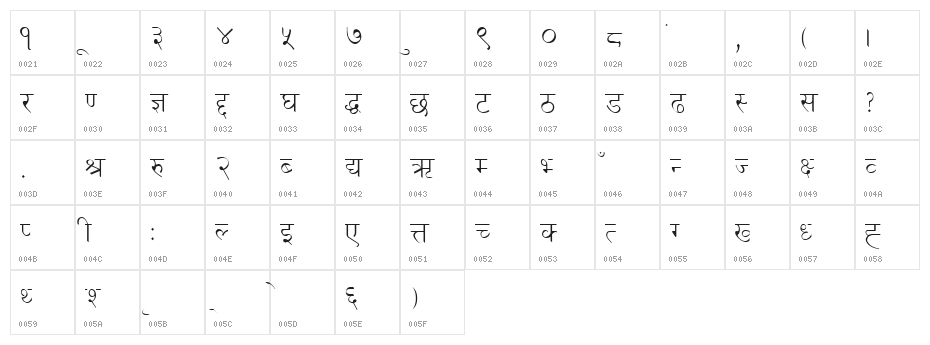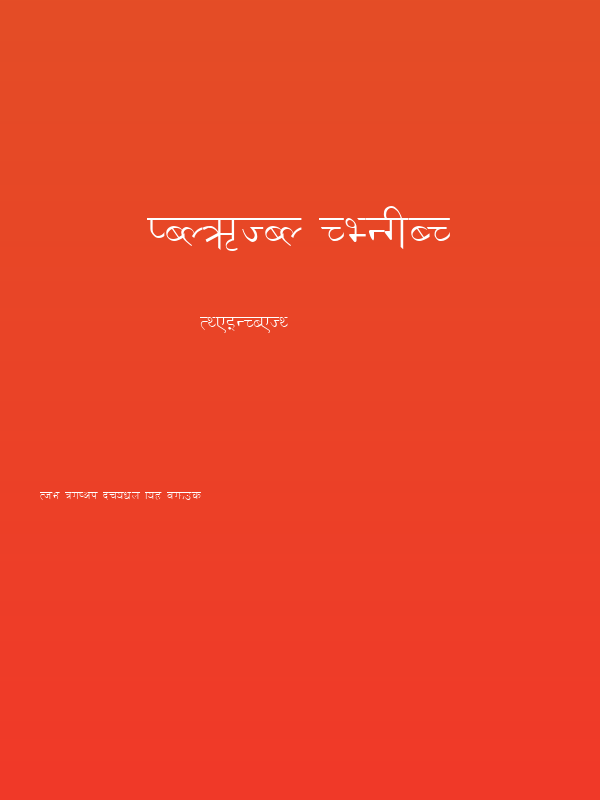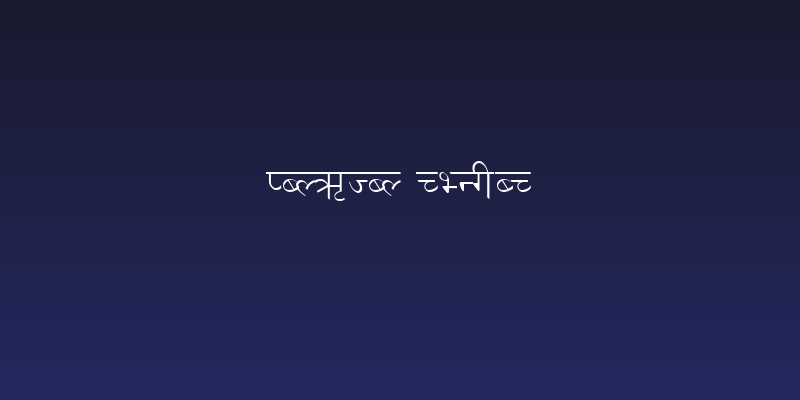
Kanchan Regular Font
✎ Calligraphic
| Категория | Calligraphic |
| Общий стиль | Classic |
| Область применения | Headlines, Artistic projects, Cultural publications |
| Рекомендуемые проекты | Ideal for cultural publications, traditional event invitations, educational materials, and artistic projects that require a touch of classic Indian aesthetics. |